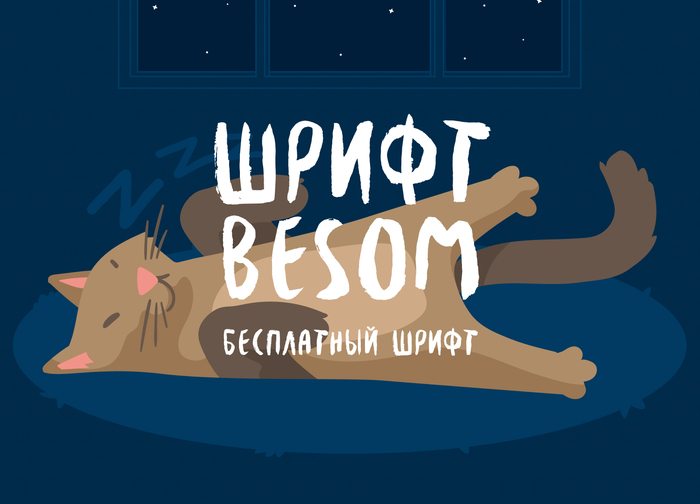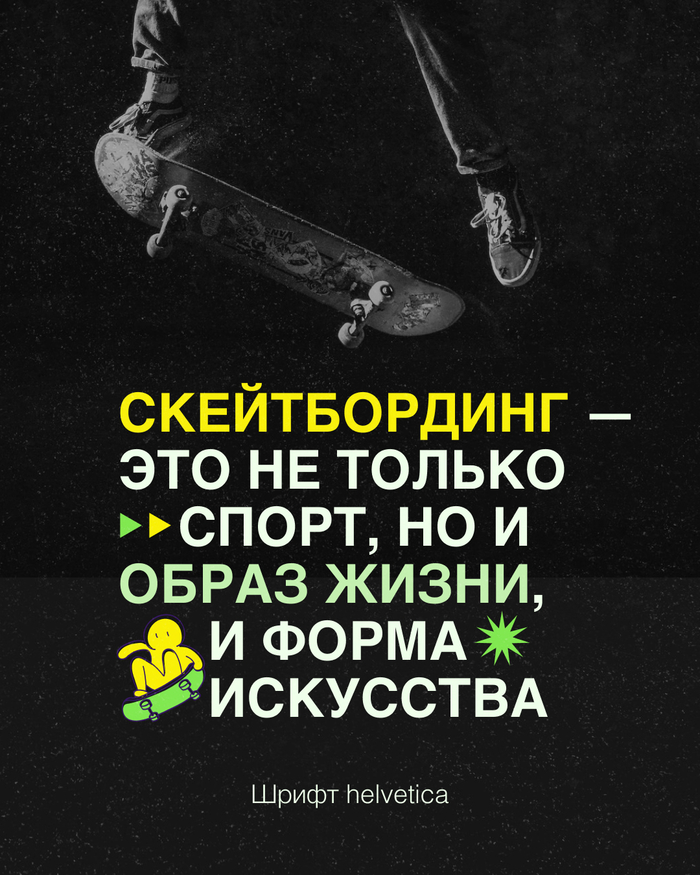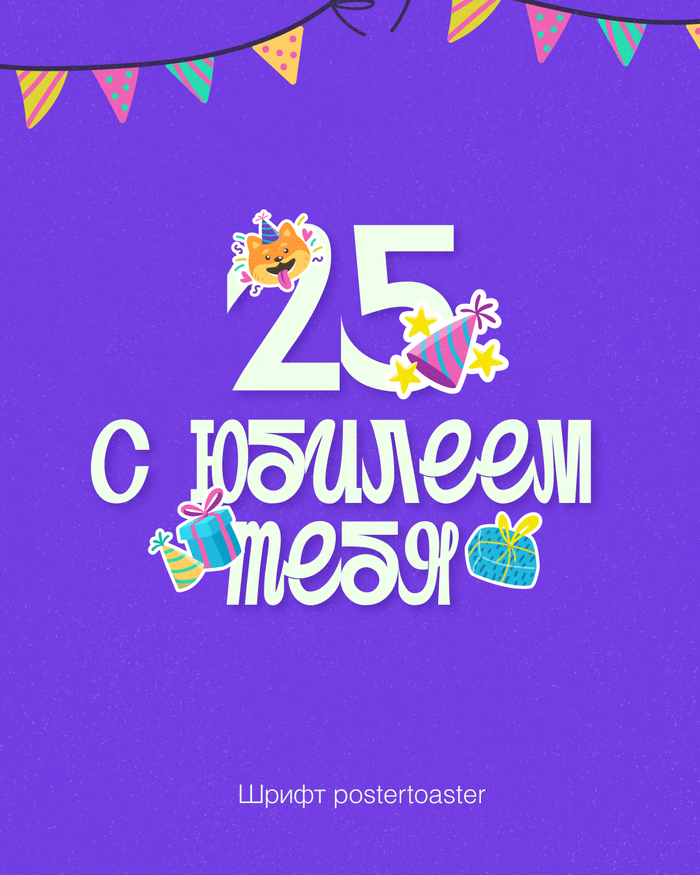
Шрифт Brushboy
Шрифт нарисованный маркером) Есть беды с написанием некоторых букв в связи с кривой кириллизацией. Но в целом приятный шрифтец.
Шрифт Caravan
Красивый рукописный шрифт. Он появился 10-м канале. 10 сентября. Красиво. Красиво
Дизайн-приёмы в типографике
Сегодня в нескольких примерах покажу интересный вариант использования текста и иконок в паре. Можно использовать как в баннерах, так и в сторис или сайтах.
Шрифт Besom. Кириллица
Besom. Шрифт нарисованный кистью. Игривый, неаккуратный) Подойдет под короткие заголовки.
Бесплатный почеркушный шрифт)
Подойдет для коротких уточняющих надписей) для заголовков он все же слишком неуверенный. А для больших объемов не сильно читаем. В примерах в презентации вы это можете заметить)
Шрифтовые запары
Сегодня очень необычная и яркая пара из двух декоративных шрифтов. Отлично впишется в игровые, детские тематики. Для примера я показал разные случаи, когда заголовком является один или другой шрифт.
Шрифт Cornerita
Полностью бесплатный шрифт. Буквы имеют форму восьмигранника. Шрифт вариативный, толщину можете настраивать сами) Отлично впишется под футуристичные тематики.